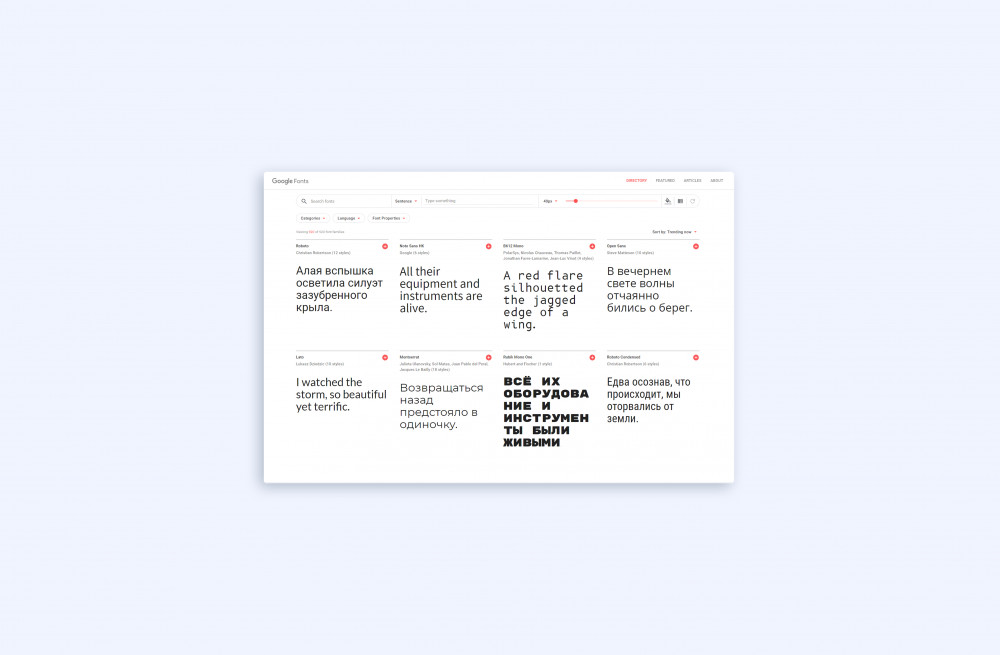
Шрифты для презентации — как подобрать и где скачать
Основная информация на слайдах передается с помощью текста. Но если его шрифт подобран неправильно, это будет отвлекать аудиторию от главной мысли и испортит всё впечатление от презентации. В этой статье мы приводим несколько рекомендаций о том, как выбрать подходящий шрифт, который украсит ваши слайды и улучшит восприятие информации.
1. Определитесь с тональностью презентации
Шрифты могут придавать слайду особое настроение. Так, шрифт Bodoni (который используется в логотипе журнала Vogue) олицетворяет роскошь и престиж, в то время как Futura придает тексту современный, даже футуристичный стиль.
2. Выберите подходящий тип шрифтов
Шрифты с засечками
Считается, что такие шрифты лучше подходят для чтения печатных материалов — взгляду проще воспринимать большие объемы текста. Также их можно использовать для больших и ярких заголовков (Baskerville, Merryweather) — шрифты с засечками помогут сформировать премиальный и более деловой стиль. Шрифты без засечек набрали популярность во времена развития электронных устройств: они просты и легче считываются с мониторов, проекционных экранов и мобильных устройств. На сегодняшний день это стандарт в графическом дизайне. Акцидентные (декоративные) Используются для написания отдельных слов, цифр и выступают в роли декоративных элементов. Отлично подходят для титульных и эмоциональных слайдов с крупным размером шрифта. Помогают создать яркий, запоминающийся стиль и передать нужное настроение. Приводим список лучших сервисов с библиотеками шрифтов. Google Fonts
3. Скачайте шрифт из библиотеки
Лучшая библиотека качественных бесплатных шрифтов. Можно выбрать тип шрифта (с засечками, без засечек и т.д.). Благодаря окну предпросмотра можно сразу набрать нужный текст и посмотреть, как он будет выглядеть с тем или иным шрифтом. В панели поиска можно установить опцию показа только шрифтов с поддержкой кириллицы.
Myfonts
Fonts.com
Adobe Fonts
Удобная синхронизация с пакетами Adobe (Photoshop, Illustrator и т.д). Для работы с сервисом требуется действующая подписка Creative Cloud (3414₽/мес.). В базе более 1600 шрифтов.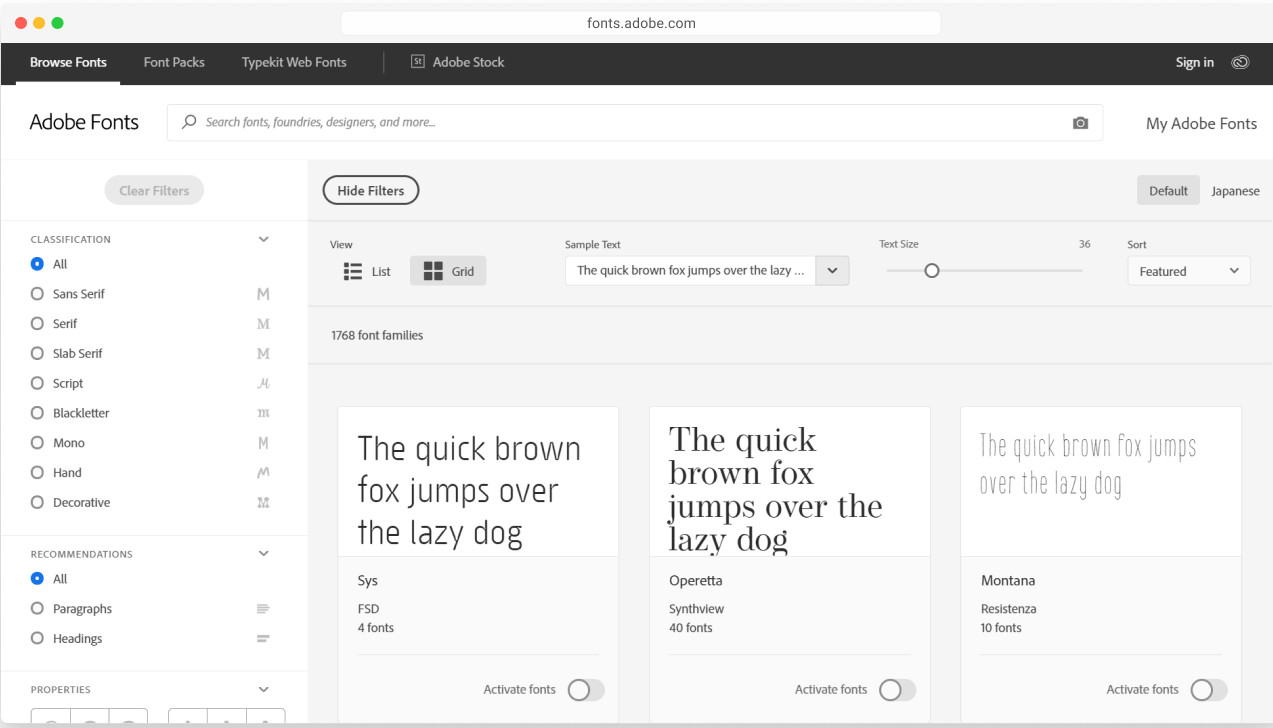